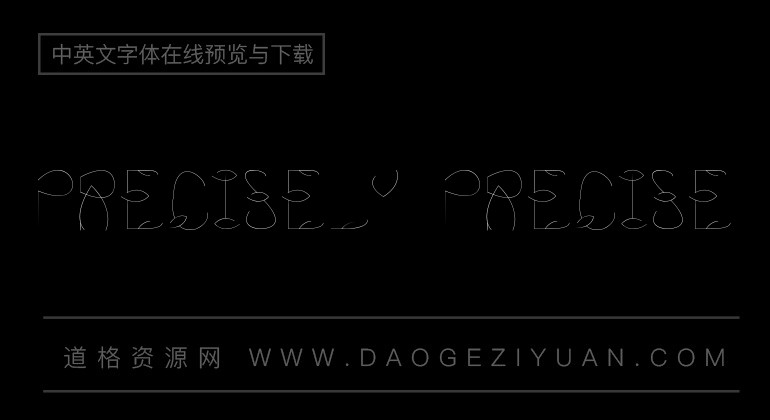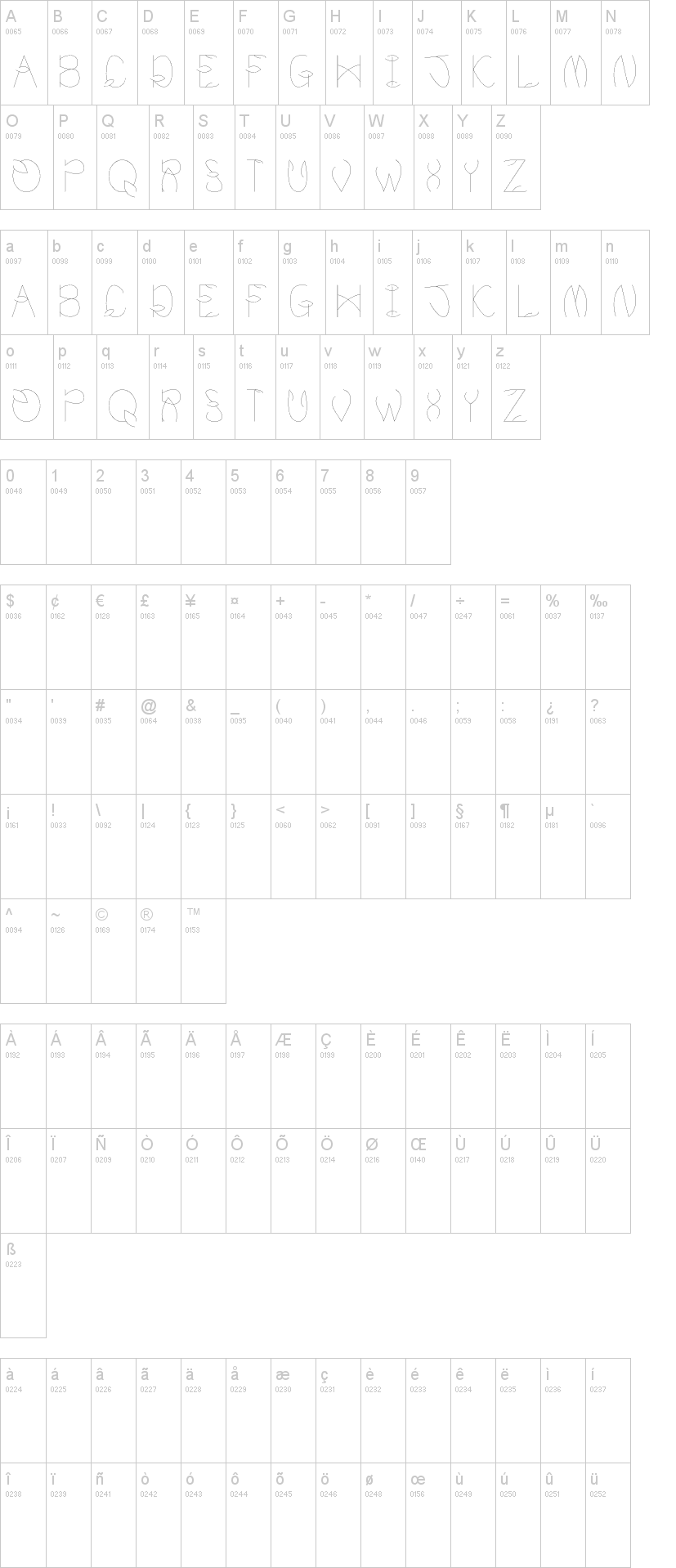
Precisely Precise
Precisely Precise 是一款简洁大方的字体,它以精细的线条结构构建出细腻而又精致的文字。它的字形具有较强的对比度,使用它可以让文字显得更加突出,更容易被阅读。另外,它的字体结构也十分简洁,可以让文字显得更加简约大方,适合用于各种不同的场合。
Precisely Precise是一款非常不错的手写艺术字体,具有很好的视觉感,适合于文化类的宣传设计、商业类品牌的广告和产品包装设计以及个性化文字排版等较多场景。